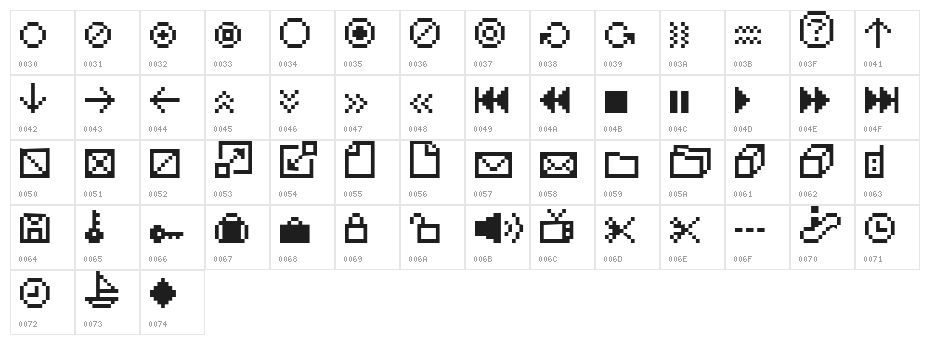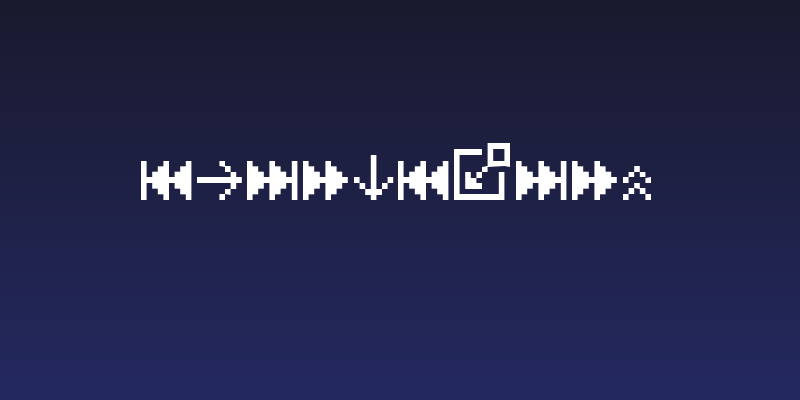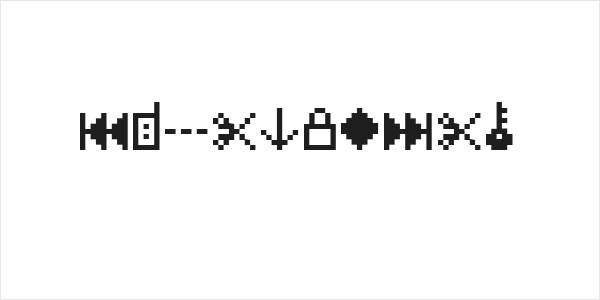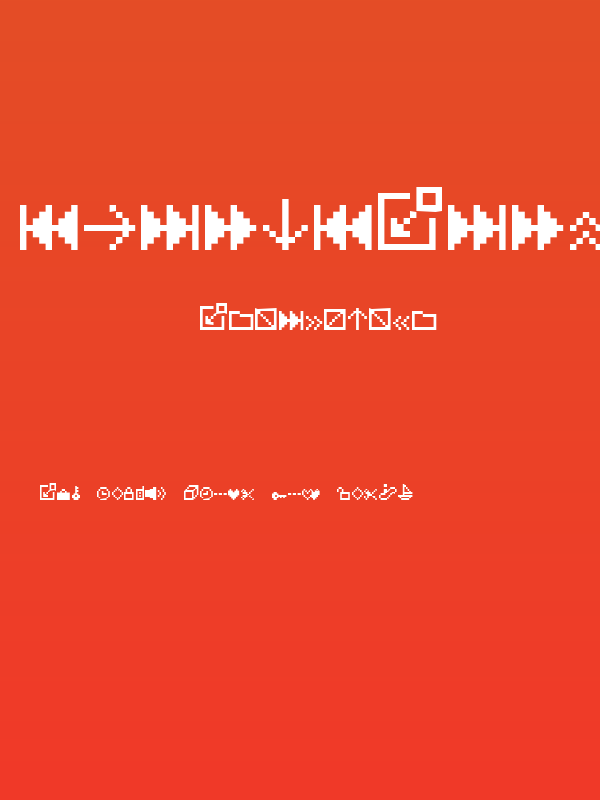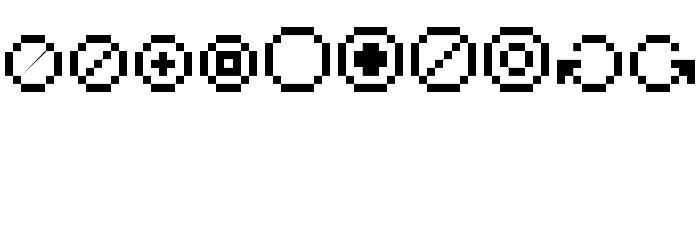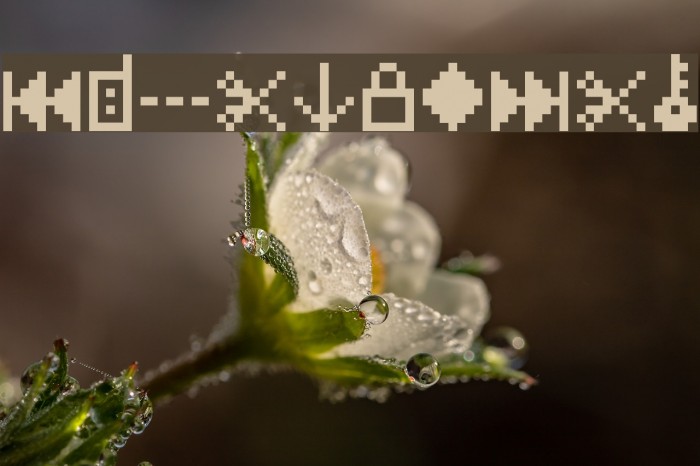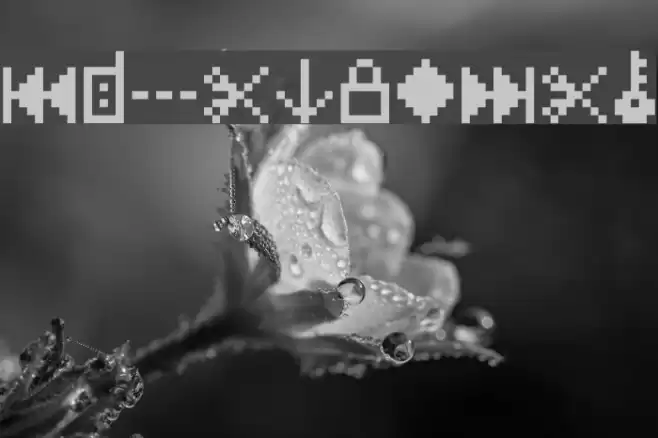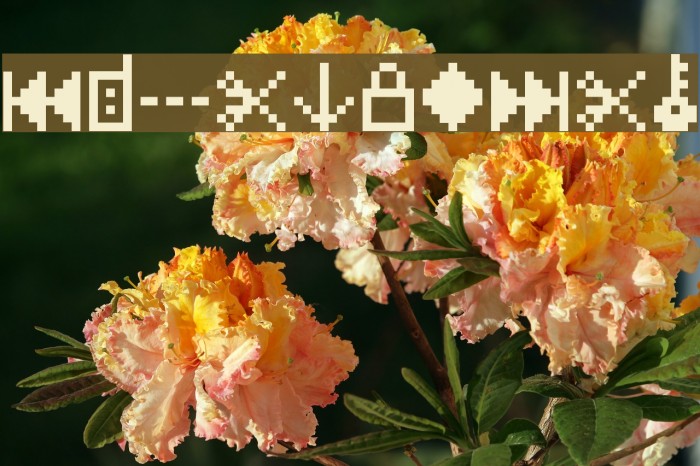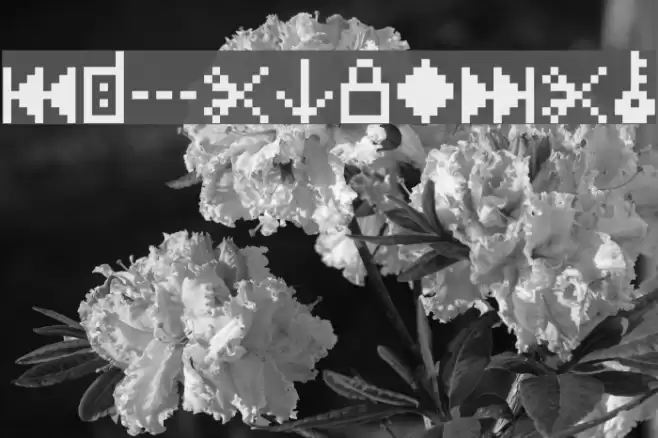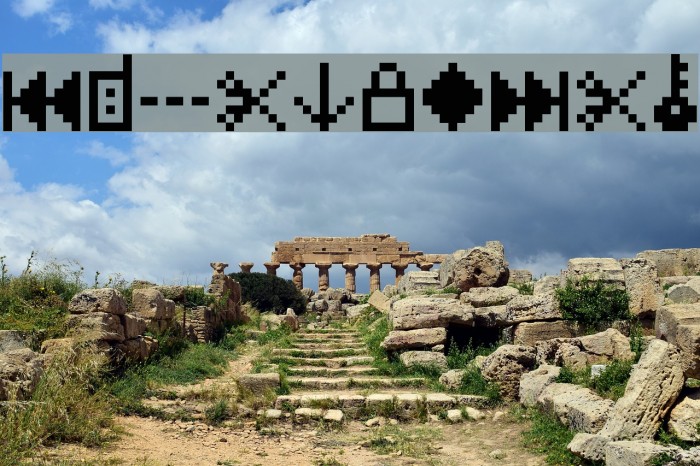
IconBitOne Font
| Estilo general | Retro, Digital |
| Caso de uso | Icons, Digital interfaces, Retro games |
| Proyectos propuestos | Ideal for retro video games, digital interfaces, or any project requiring a pixel art aesthetic. |